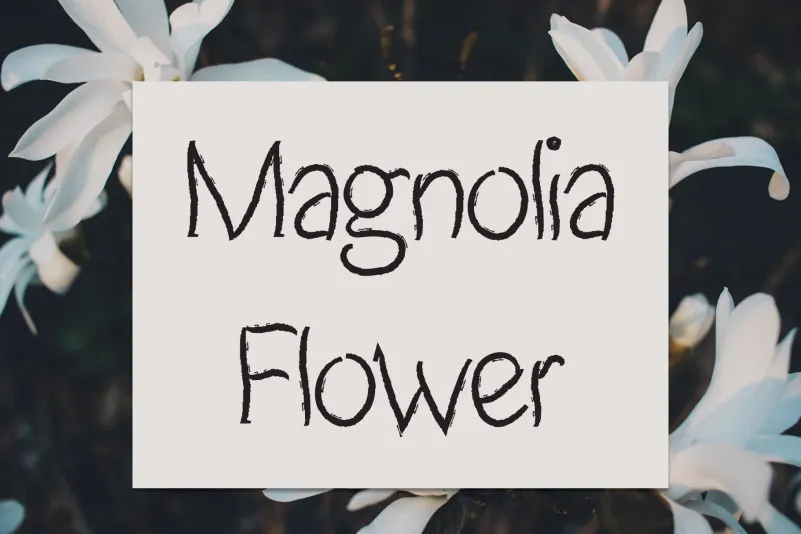
Magnolia Flower Script Font – Fonte Grátis
Magnolia Flower Script Font
Magnolia Flower Script Font é uma fonte a mão que traz leveza e delicadeza à sua escrita digital. Simplesmente ao toque do pincel, seu traço fluido evoca imagens de flores magnólias doces e suaves. Esta fonte perfeita para textos decorativos e personalizados pode ser usada em rótulos de produto, nomes de lojas ou até mesmo para criar cartões personalizados. Com seus traços delicados e elegantes, Magnolia Flower Script é uma escolha natural para qualquer designer gráfico que busca um toque feminino e suave. Esse foi o motivo pelo qual a fonte se tornou tão popular, se tornando seu favorito por diversas razões, seja para nomes de lojas românticos ou textos em formatos mais formais. Suas curvas suaves e traços delicados fazem com que Magnolia Flower Script seja uma excelente escolha para trabalhos onde um toque de feminilidade e delicateza é desejado. Ideal tanto para o design gráfico quanto para a criação de produtos personalizados, esta fonte oferece um toque delicado que torna seu trabalho único e especial.